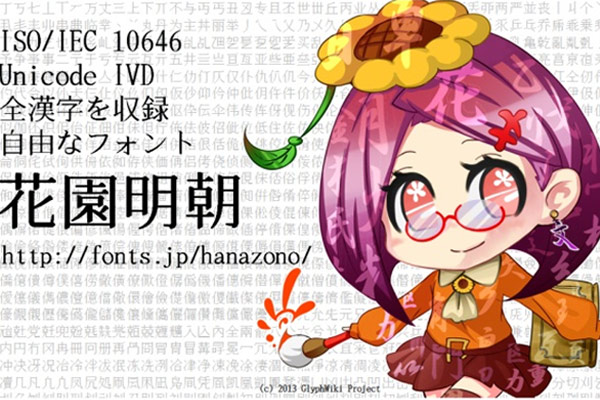
明朝体和宋体有什么区别吗?
明朝体和宋体在很多情况下所指相同,但也存在一些细微差别。
一、概念范围
“宋体” 是一种较为通用的字体名称,涵盖了从宋代刻本字体发展而来的一大类字体风格,历经多个朝代的演变和发展。
“明朝体” 有时候也称明体,在日本使用较多,主要指在明朝时期传入日本的刻本字体风格经过日本本土化发展后的字体类型。在日本,“明朝体” 概念相对更具体地指向特定风格的一类字体。
二、字体风格特点
1. 笔画细节:
• 宋体:笔画有粗细变化,横细竖粗较为明显。笔画末端有装饰性的三角形 “顿角”,如横画末端的三角形较为规整。点、撇、捺、钩等笔画也有特定的装饰性处理。
• 明朝体:同样有横细竖粗的特点,但在笔画的装饰性上可能与宋体略有不同。其笔画末端的顿角可能在形状、大小上与宋体有所差异,相对来说可能更加精致细腻一些。
2. 字体结构:
• 宋体:字体结构较为方正稳重,各个笔画的布局相对均衡,给人一种端庄大气的感觉。
• 明朝体:在结构上可能更加注重比例的协调性和线条的流畅性,整体感觉更加优雅。
3. 字面大小:
• 宋体:字面大小相对较为适中,在排版中能够较好地适应不同的文本内容和排版需求。
• 明朝体:字面可能会稍小一些,在排版时会给人一种较为紧凑、精致的视觉效果。
三、应用场景
1. 宋体:在中国大陆及其他一些地区广泛应用于各类印刷品、电子文档、广告宣传等领域。由于其具有较高的辨识度和易读性,适合用于长篇文本、正式文件、书籍排版等。例如政府公文、学术论文、报纸杂志等通常会使用宋体字体。
2. 明朝体:在日本主要用于书籍、报纸、杂志等印刷品,以及一些正式的文件和宣传资料中。在设计领域,明朝体也常被设计师用于营造复古、优雅的氛围,或者用于体现高品质、精致的设计风格。例如一些日本的传统文化宣传海报、高端品牌的包装设计等可能会使用明朝体。